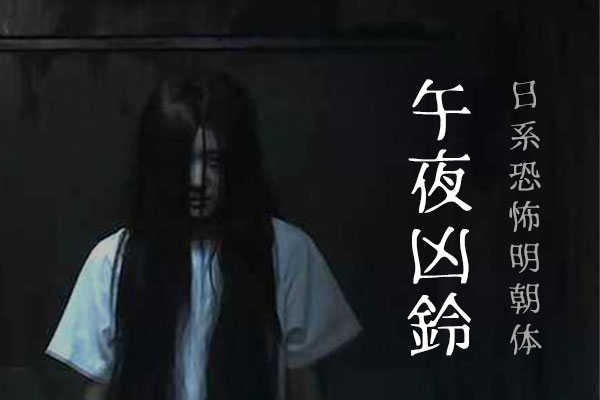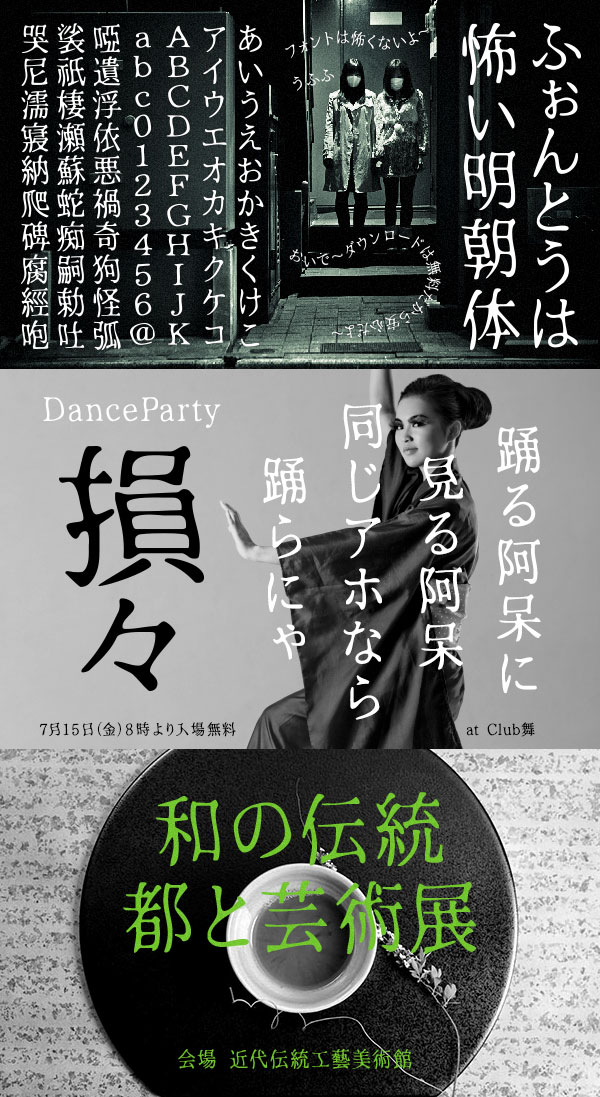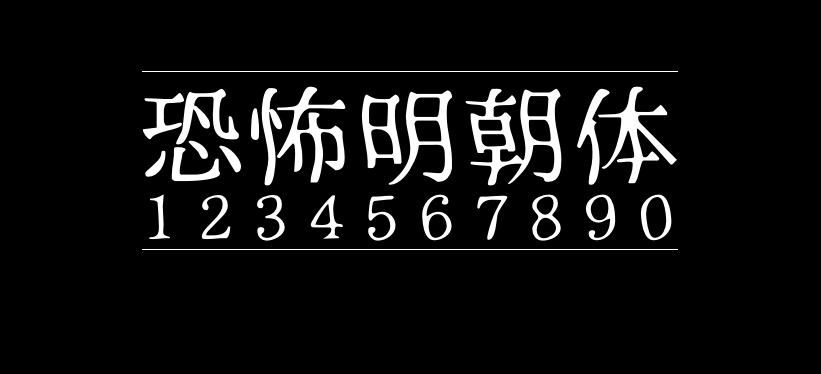
恐怖明朝体
恐怖明朝体(07ふぉんとうは怖い明朝体/07ReallyScaryMinchotai)是一款来自日本的免费字体,它可以用于商业和非商业目的。
恐怖明朝体是一种奇怪的字体,带有轻微破碎的印象。想象一下一个典型的日本恐怖电影/恐怖小说,但是由您决定该字体是恐怖还是轻柔。
虽然是来自日本的字体,但是该字体对中文的支持还是不错的,简体有缺字现象,繁体支持得比较好,究竟怎么样下载试试吧!